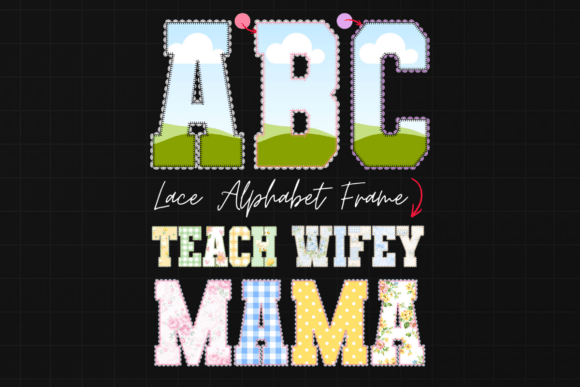
Lace Alphabet Canva Font Frame Template
Conçu avec précision, Lace Alphabet Canva Font Frame Template offre des vecteurs nets, une typographie fluide et une licence commerciale pour une tranquillité d'esprit.